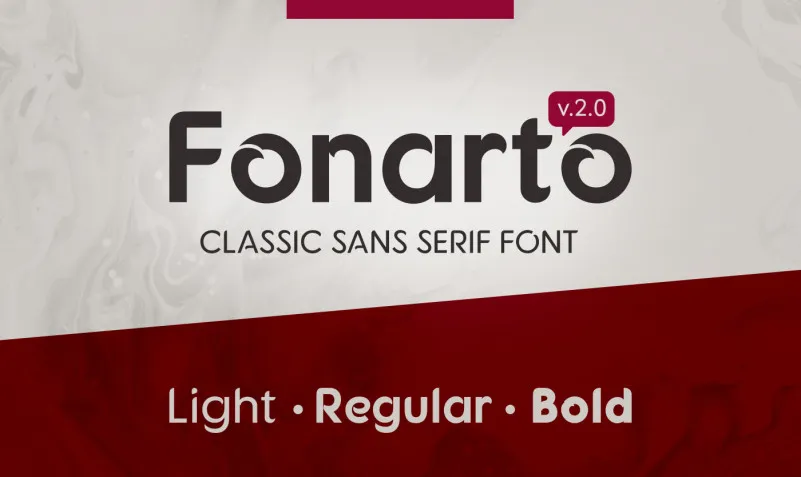
Fonarto v.2.0 Sans Font Family – Download Grátis
Agradeçemos por olhar a fonte Fonarto v.2.0. Esta é uma fonte sans-serif clássica desenvolvida sobre baseada na primeira versão do famoso famoso família de fontes Fonarto criado pelo autor. Com um estilo único, ela se destaca entre as demais e atende às necessidades de qualquer ideia que você possa trazer para este período moderno. Inspirada no estilo atualmente popular, essa fonte ajuda você a criar designs desportivos e elegantes, perfeitamente adequados para design de necessidades como cartões de visita, folders, revistas e outros projetos de design com temas desportivos. Com Fonarto v.2.0 Font Family, sua criatividade pode ganhar vida em um estilo sofisticado que se encaixa perfeitamente em ambientes profissionais e modernos.